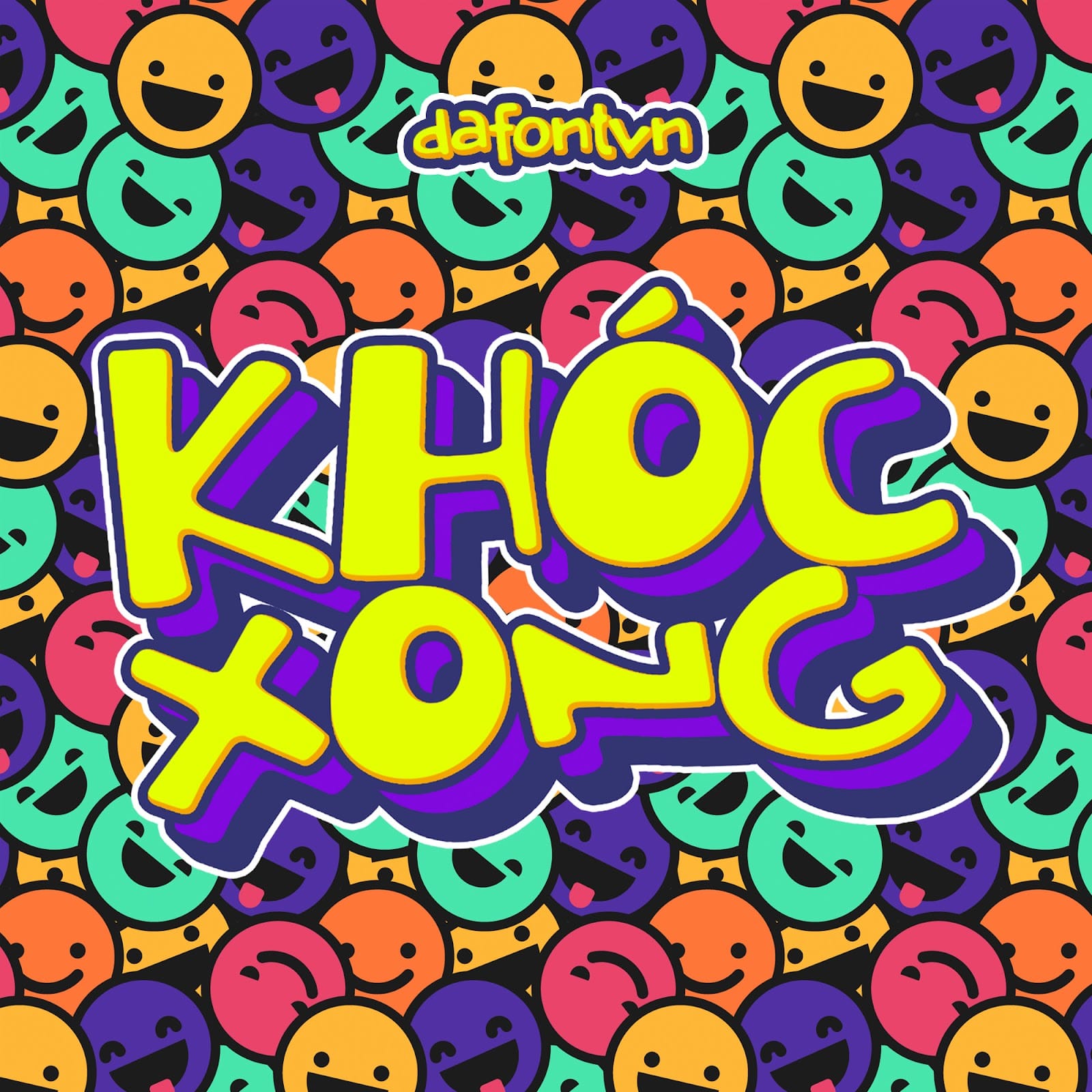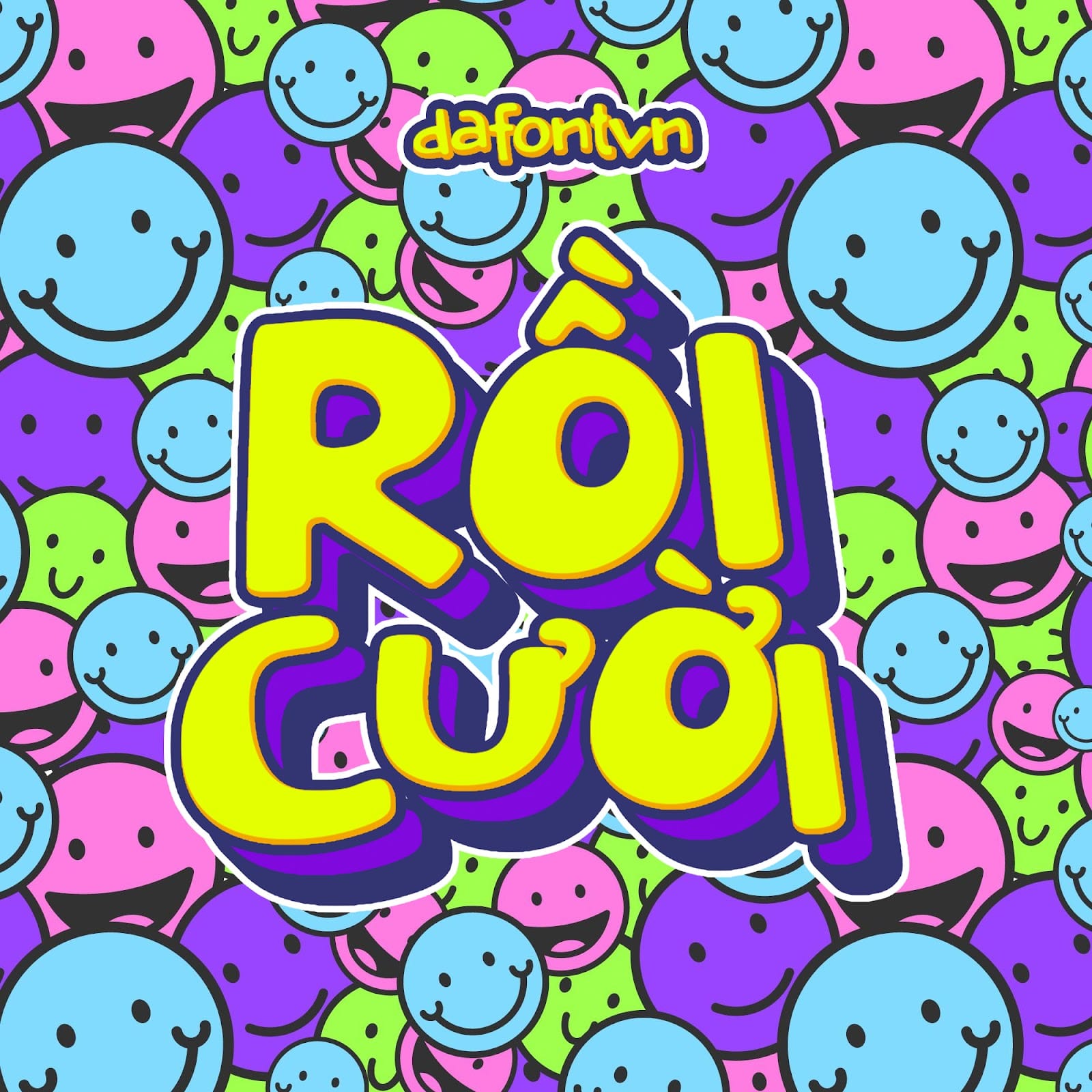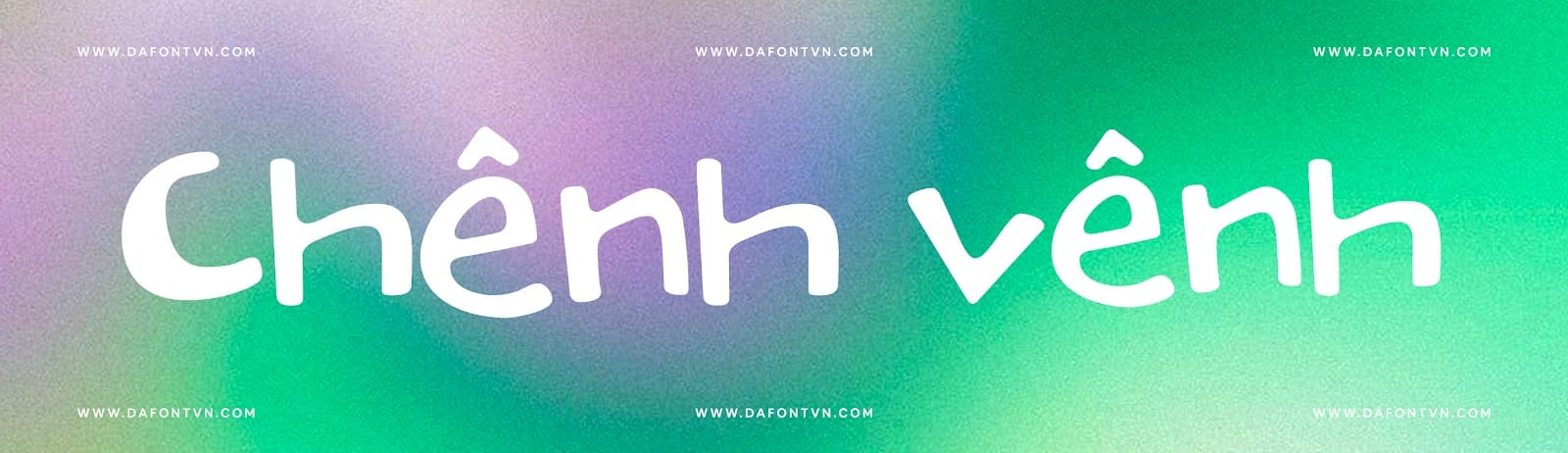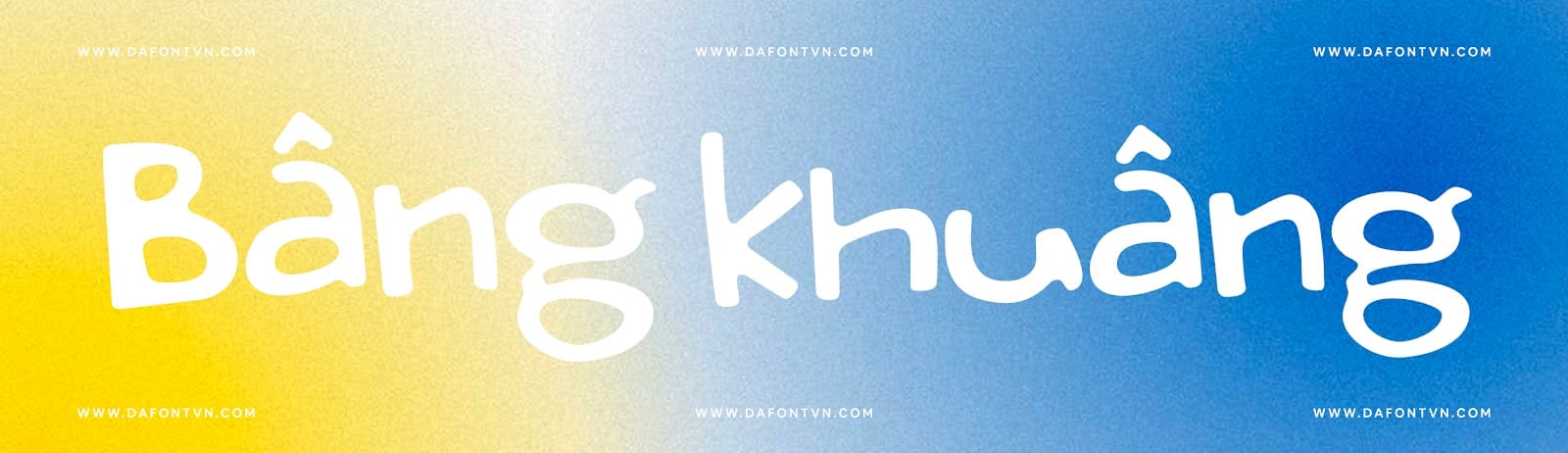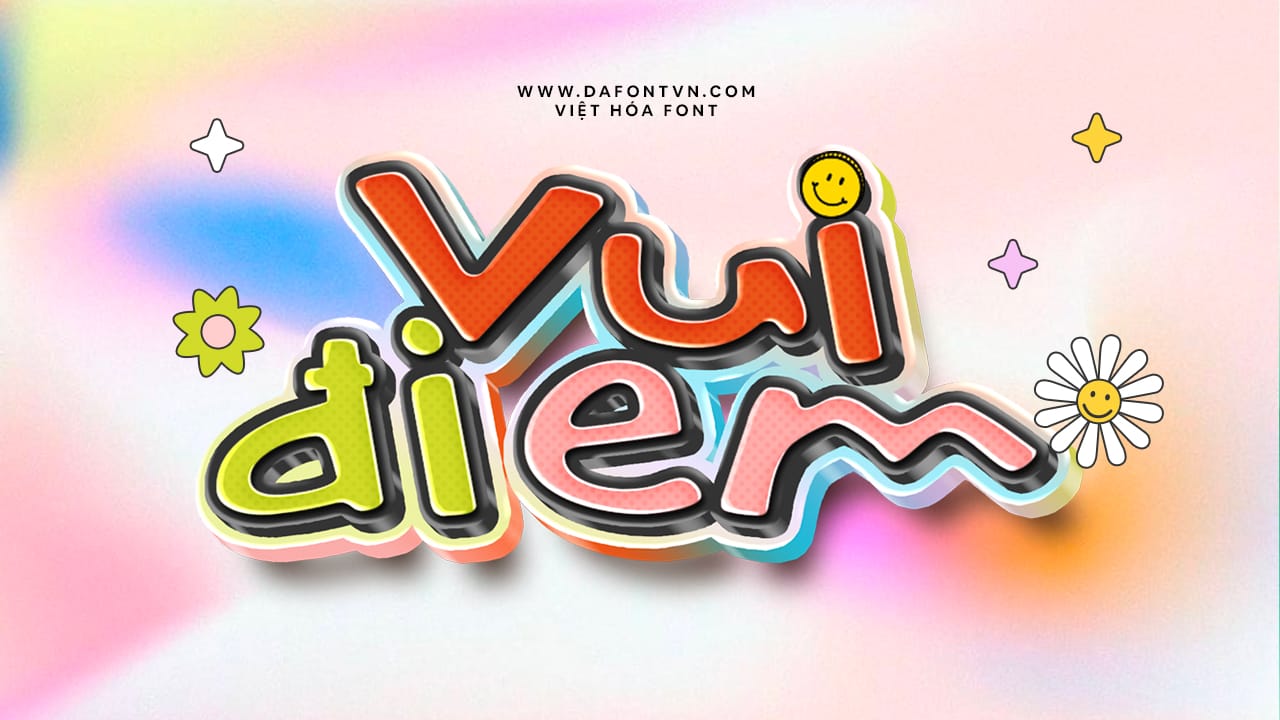
Orenji là từ tiếng Nhật, bản dịch phiên âm tiếng Anh là Orange. 1 kiểu font với vẻ ngoài vui tươi, dễ thương đúng như tên gọi của nó (như 1 quả cam ngọt ngào). Font chữ này được tác giả thử nghiệm dựa trên ý tưởng tạo ra một phông chữ viết tay của con trai ông.
Orenji là một font chữ vui nhộn, dễ thương và xa hoa. Các ký tự được thiết kế có hình dạng độc đáo, giống như một tiếng cười khúc khích, một cái ôm ấm áp. Font có cả ký tự thường và ký tự hoa, các ký tự được thiết kế không đồng nhất, nó giống như một kiểu chữ viết tay nguệch ngoạc.
Đây là một font chữ rất đẹp để sử dụng cho các thiết kế như bìa truyện, thiệp mời, trang trí hoặc bất kỳ thiết kế nào cần một kiểu font viết tay vui nhộn.